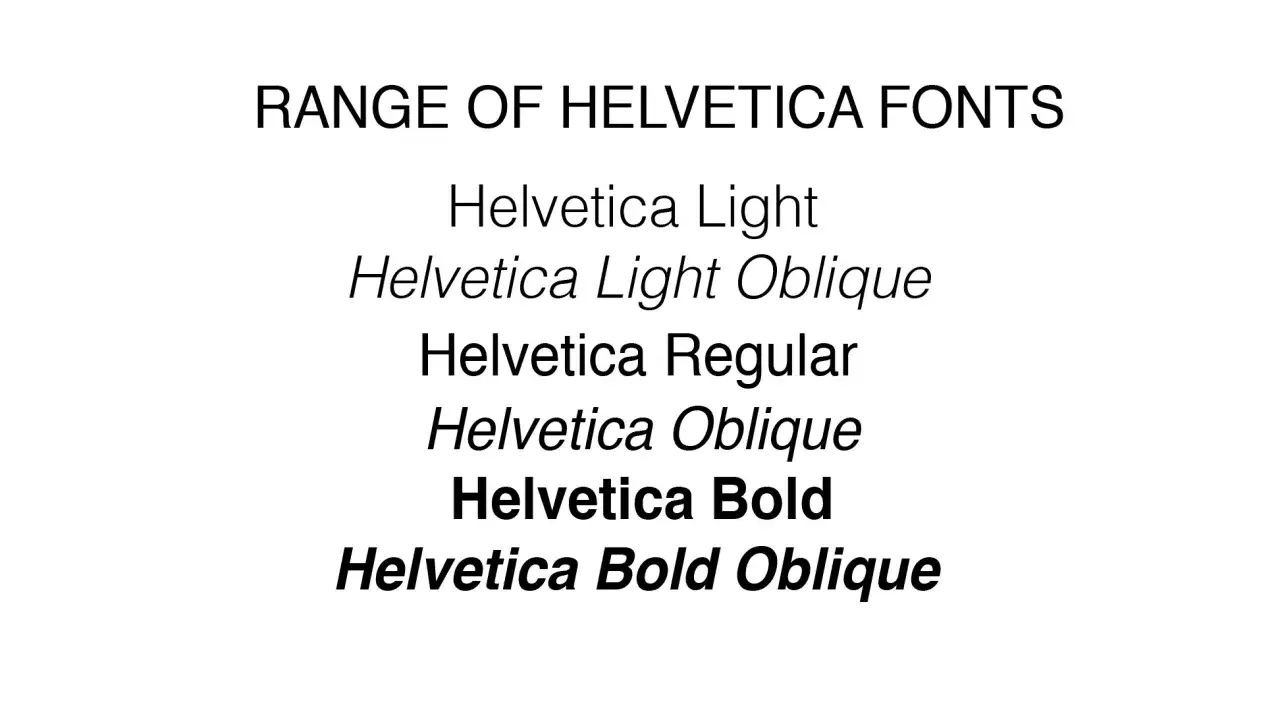
Typografia na stronie - Co naprawdę poprawia czytelność?
Typografia decyduje o tym, czy treść jest skanowana w kilka sekund, czy czytana do końca. W praktyce przekształcanie tekstu oznacza tu nie tyle zmianę samych słów, ile świadome sterowanie wyglądem: krojem pisma, wielkością, interlinią, odstępami i zapisem liter. Dobrze ustawiony tekst prowadzi wzrok bez wysiłku, a źle dobrany potrafi zabić nawet mocną treść.
W tym artykule pokazuję, jak dobierać fonty, kiedy używać wersalików, co naprawdę poprawia czytelność na stronie i jakie błędy najczęściej psują efekt. To przyda się zarówno przy blogu, jak i przy sklepie internetowym czy landing page'u, gdzie każda sekunda uwagi ma znaczenie.
Co naprawdę poprawia czytelność tekstu na stronie
• Font to tylko jeden element - równie ważne są interlinia, długość wersu i kontrast.
• Tekst główny zwykle najlepiej startuje od 16-18 px i interlinii 1.5-1.6.
• Do dłuższych treści wystarczą najczęściej 1-2 kroje pisma.
• Wersaliki sprawdzają się w krótkich etykietach, ale męczą w dłuższym tekście.
• Sentence case jest zwykle naturalniejszy dla polskich stron niż agresywne kapitalizowanie nagłówków.
• Typografia wpływa nie tylko na estetykę, ale też na dostępność i tempo czytania.
Co naprawdę zmieniasz, gdy poprawiasz tekst na stronie
Gdy mówię o typograficznej obróbce treści, myślę o trzech poziomach. Pierwszy to sam zapis słów: wielkość liter, format nagłówka, skróty i wersaliki. Drugi to warstwa wizualna: krój pisma, rozmiar, grubość, odstępy, wyrównanie. Trzeci to odbiór: tempo czytania, hierarchia informacji i wrażenie, jakie zostaje po wejściu na stronę. W języku potocznym mówi się często "czcionka", ale przy projektowaniu stron wolę mówić o kroju pisma lub foncie, bo to po prostu precyzyjniejsze.
To ważne rozróżnienie, bo wiele osób skupia się tylko na "ładnym fontcie", a potem dziwi się, że tekst nadal męczy. Sama zmiana kroju nie naprawi zbyt długich akapitów ani za małego kontrastu. Z kolei dobrze zbudowana typografia potrafi podnieść jakość treści bez zmiany ani jednego zdania.
W praktyce zawsze zaczynam od pytania, czy celem jest tylko lepszy wygląd, czy też szybsze przyswajanie informacji. Od tej odpowiedzi zależy, jak daleko idzie później cały system fontów i formatowania.
Przekształcanie tekstu: różne kroje pisma Helvetica, od Light po Bold Oblique, pokazujące subtelne zmiany w grubości i pochyleniu.
Jak fonty wpływają na odbiór treści
Font nadaje ton, zanim czytelnik przeczyta pierwsze zdanie. Krój szeryfowy zwykle kojarzy się z tradycją, bezszeryfowy z prostotą i nowoczesnością, a display z mocnym charakterem. Monospace działa technicznie i bywa świetny w blokach kodu, ale w długim tekście potrafi męczyć. Coraz ciekawszą opcją są fonty zmienne, które pozwalają płynnie regulować grubość i szerokość znaków bez przeładowywania strony wieloma plikami.
W projektach internetowych najważniejsze jest jednak nie to, czy font jest "modny", tylko czy pasuje do treści. W sklepie z elektroniką sprawdzi się coś czystego i neutralnego. W serwisie premium można pozwolić sobie na bardziej wyrazisty krój, ale nadal trzeba pilnować czytelności. Z ozdobnymi fontami pracuję ostrożnie, bo przy małym rozmiarze szybko tracą charakter i zamieniają się w dekorację bez funkcji.
Rodzaj kroju Gdzie działa najlepiej Ryzyko
Bezszeryfowy Treści internetowe, interfejsy, e-commerce Może wyglądać zbyt neutralnie, jeśli całość jest bez wyrazu
Szeryfowy Artykuły, treści eksperckie, marki premium Przy złym doborze staje się cięższy w małych rozmiarach
Display Short hero, plakaty, nagłówki Nie nadaje się do długiego czytania
Monospace Kod, dane techniczne, cytaty techniczne Zajmuje dużo miejsca i obniża komfort długich akapitów
Variable font Nowoczesne strony z większą kontrolą nad wagą i szerokością Wymaga sprawdzenia wsparcia i sensownego wdrożenia
Dobry font nie musi przyciągać uwagi sam z siebie. Najlepiej działa wtedy, gdy wspiera treść, a nie z nią konkuruje. I właśnie dlatego po wyborze kroju przechodzę od razu do parametrów, które najbardziej wpływają na komfort czytania.
Parametry, które robią większą różnicę niż sam wybór fontu
W typografii internetowej najczęściej wygrywa nie najbardziej efektowny krój, tylko sensowne ustawienia. Z mojego doświadczenia to właśnie interlinia, długość wersu i kontrast decydują o tym, czy tekst "płynie", czy się rozsypuje. Dobrze ustawiony krój przeciętnej urody będzie czytany chętniej niż piękny font użyty bez umiaru.
Element Bezpieczny punkt startowy Co się dzieje, gdy przesadzisz
Rozmiar tekstu głównego 16-18 px Za mały męczy wzrok, za duży rozrywa rytm akapitów
Interlinia 1.5-1.6 Za mała skleja wiersze, za duża rozbija ciąg czytania
Długość wersu 45-75 znaków Zbyt długi wers utrudnia powrót do początku następnej linii